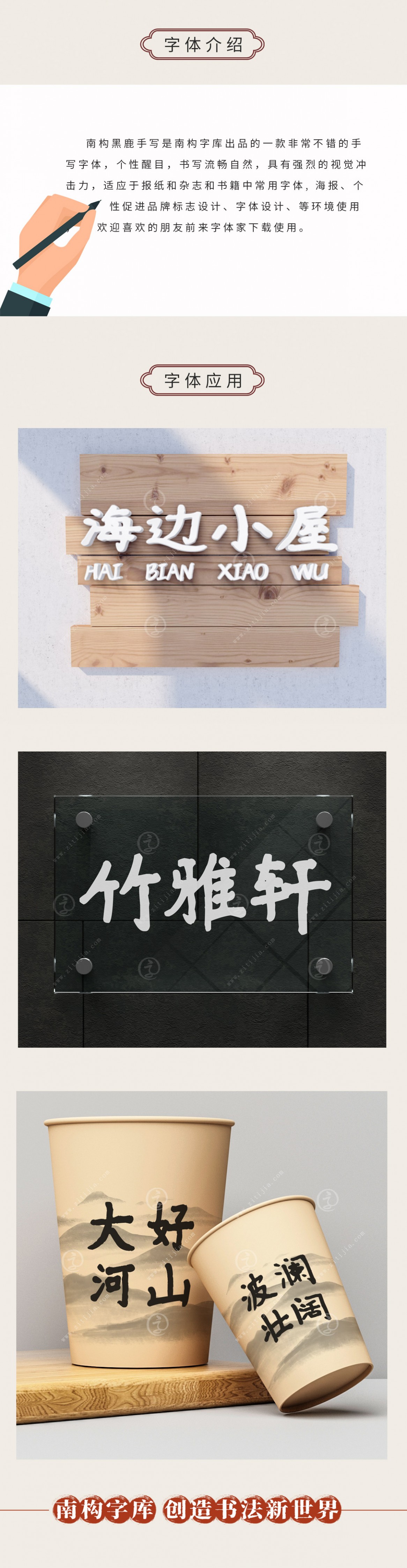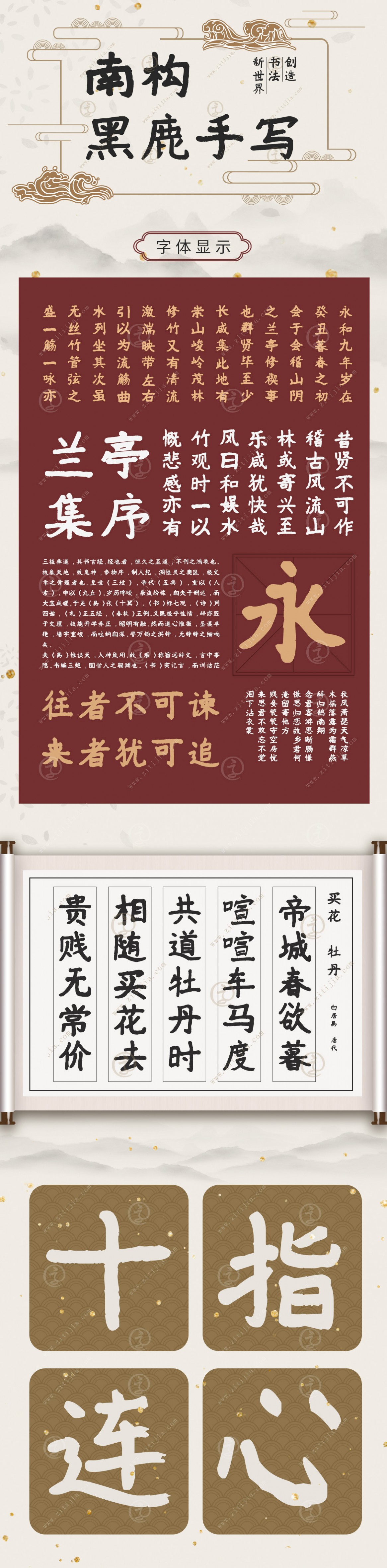
南構(gòu)黑鹿手寫
南構(gòu)黑鹿手寫是南構(gòu)字庫出品的一款非常不錯(cuò)的手寫字體,個(gè)性醒目,書寫流暢自然,具有強(qiáng)烈的視覺沖擊力,適應(yīng)于報(bào)紙和雜志和書籍中常用字體, 海報(bào)、個(gè)性促進(jìn)品牌標(biāo)志設(shè)計(jì)、字體設(shè)計(jì)、等環(huán)境使用,歡迎喜歡的朋友前來字體家下載使用。